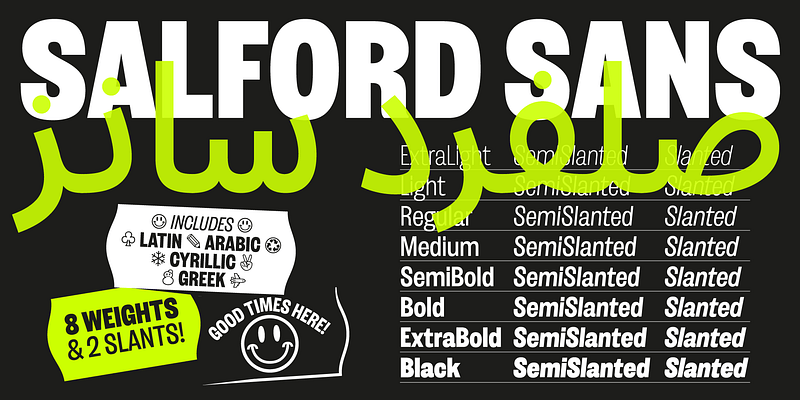
Salford Sans には 8 つの太さ、傾斜と半傾斜のスタイルがあり、広範なラテン文字、単調なギリシャ文字、アラビア文字、キリル文字の 4 つのスクリプトをカバーしています。真面目で国際的かつコミュニカティブでありながら、スタイリッシュでハンドメイドといった個性を残す必要がある見出し、エディトリアル、ディスプレイワークなどに最適です。シンボル、整然とした機能、バリアブル傾斜軸、様々な現地語機能が詰まった Salford Sans は、伝統的な英国スタイルのコンデンスサンセリフに基づいています。堅牢で機能的かつエレガントなコンデンスサンセリフであり、世界中で通用する古典的なアイデアをアップデートしたものです。